フォントを作る人に聞いてみた その1:書体デザインに興味を持ったきっかけ1
タイププロジェクトのスタッフ達に「書体デザインに興味を持ったきっかけ」は何かを聞いてみました。
今回の記事では書体デザイナーの回答の中で一番多かった、学生時代の授業がきっかけだったというコメントを紹介します。
- 大学1年生のタイポグラフィの授業。小学生の頃から「多くの人が日常的に使うものを作りたいな」という気持ちがあって、プロダクト系を考えたりした時期もありました。それが書体デザインに繋がったのは大学1年生のタイポグラフィの授業です。
- 黒板のノート書き写しや漢字の書き取りが面白かったことや、大学時代の活版実習が楽しかったことから興味を持つようになりました。活版実習の時に教授と話して書体デザイナーの仕事を知りました。
- 大学での授業。もともと潜在的に興味はあったが授業で学ぶことではっきりした。
- 学生時代に小塚昌彦さんの講義を聴いたことがきっかけです。スクリーンに大写しになった欧陽詢の楷書が強く印象に残りました。
- 大学の授業がきっかけで書体デザインという仕事に興味を持った。中高時代からノートの表紙にレタリングをしたり本やCDのタイトルロゴを模写してみたりしていたが、レタリング・ロゴデザインと書体デザインというジャンルが別物であること、普段パソコンやスマホで使っている書体も一文字一文字デザイナーが制作していると言うことを大学のタイポグラフィの授業を通して知った。
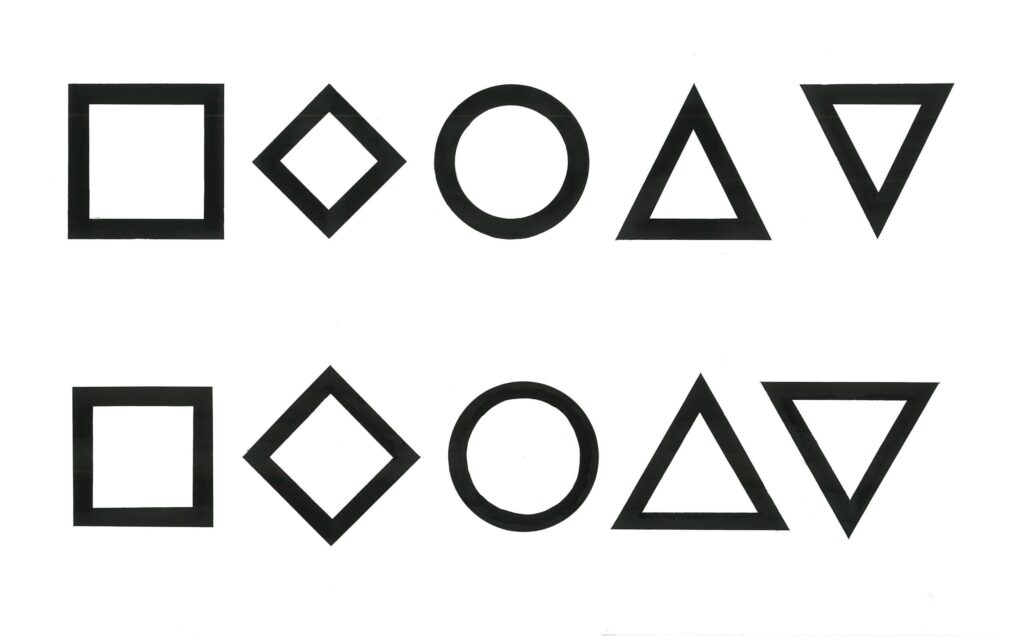
視覚調整の課題
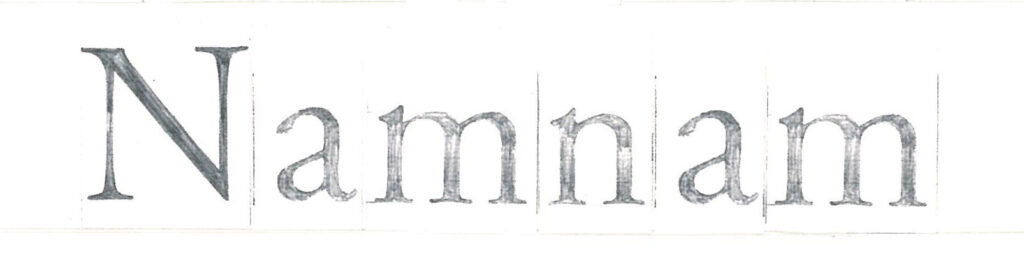
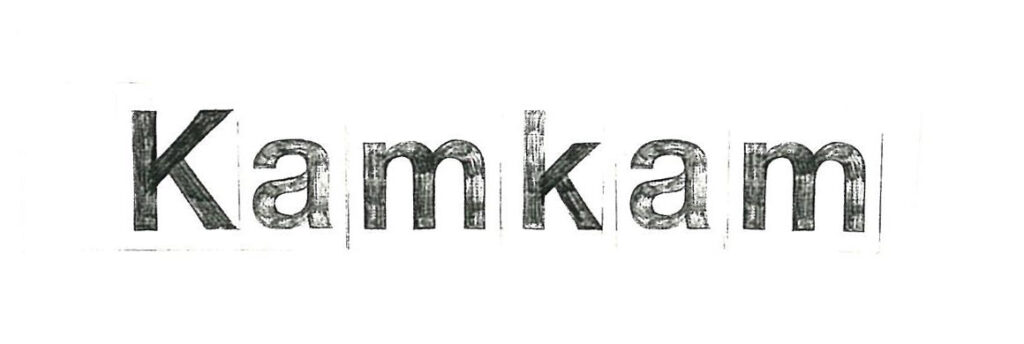
欧文スペーシングの課題
デザイナーのほとんどは美術系大学の出身なのでそこでのタイポグラフィ関連の授業などから影響を受けた人が多いようですが、これらの回答を見ると「知る機会・学ぶ機会」があることの大切さを感じます。
普段の生活の中で書体を見たり使用したりする機会は多いですが、それらが作られる工程や作り手が表に出る機会は決して多くありません。今回の回答にあるような書体デザインを知るきっかけとなっている授業や講演会が増え、より多くの人に興味を持ってもらえることを願っています。